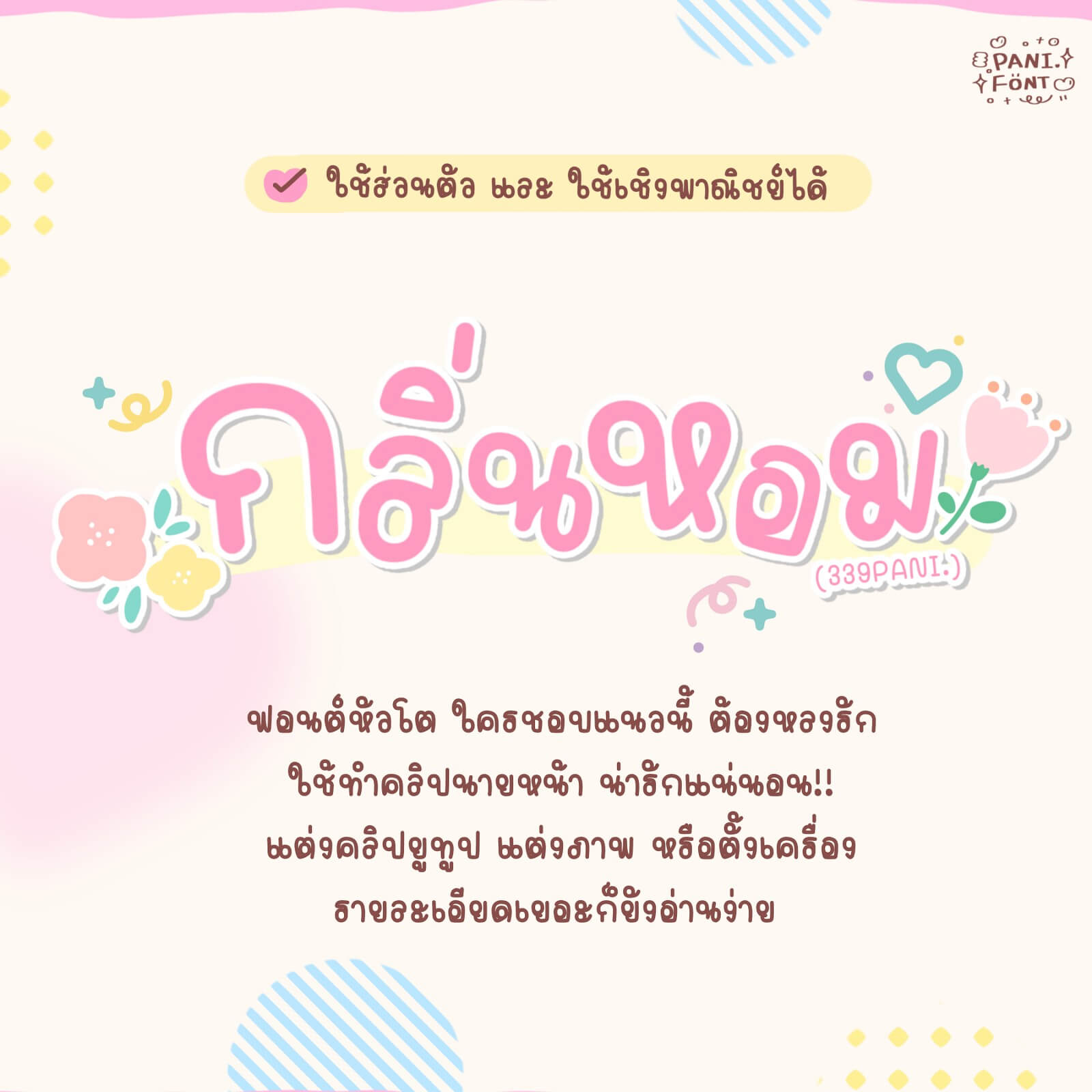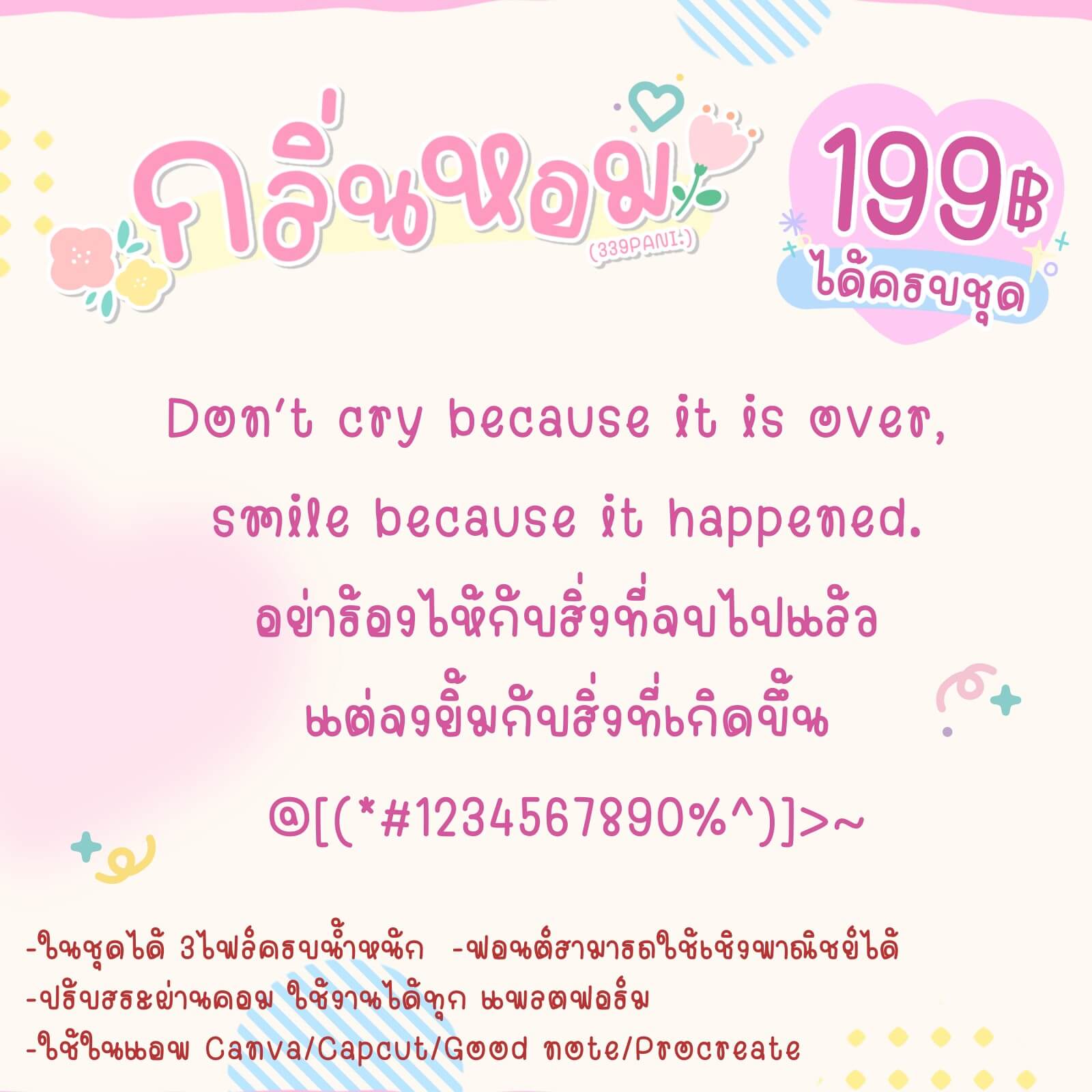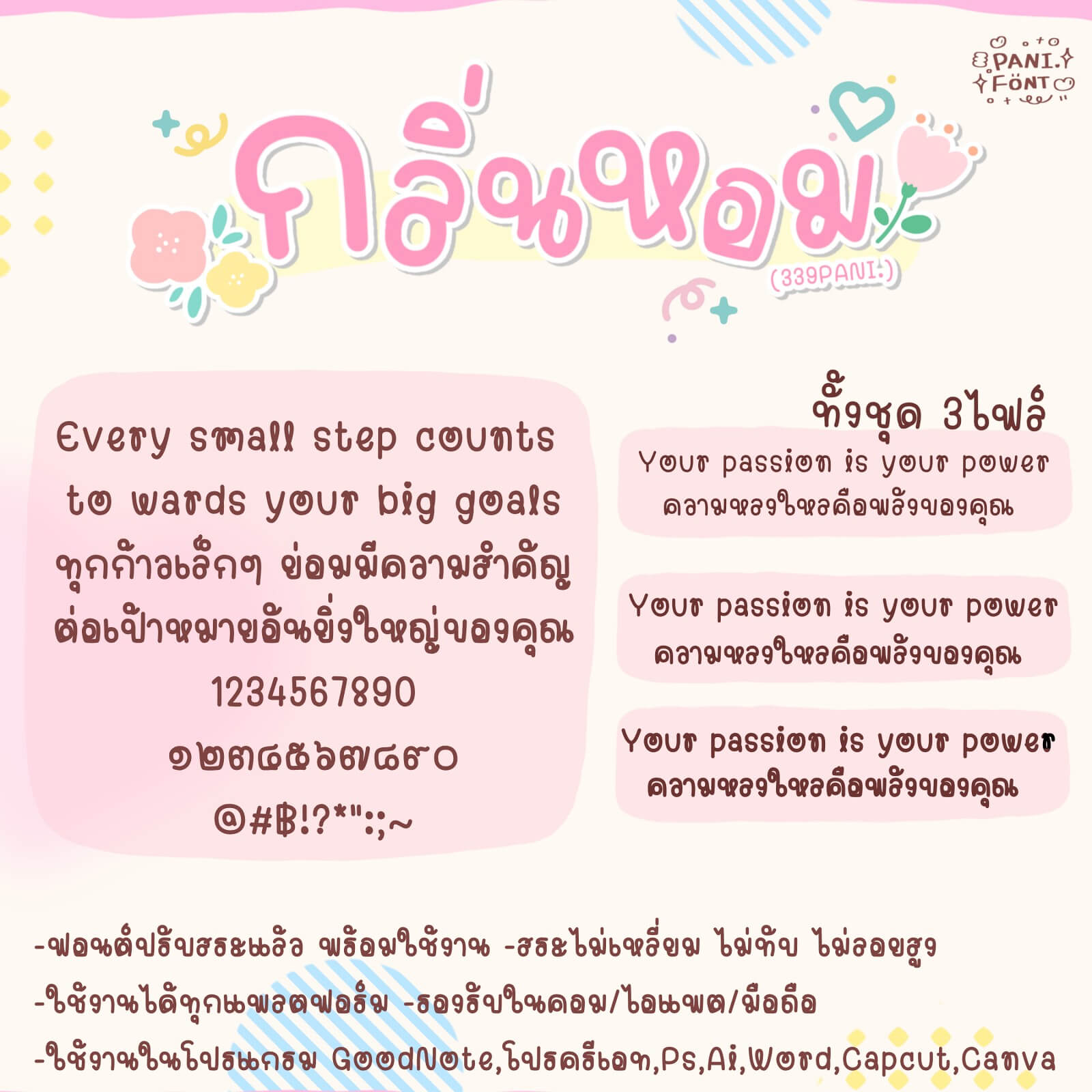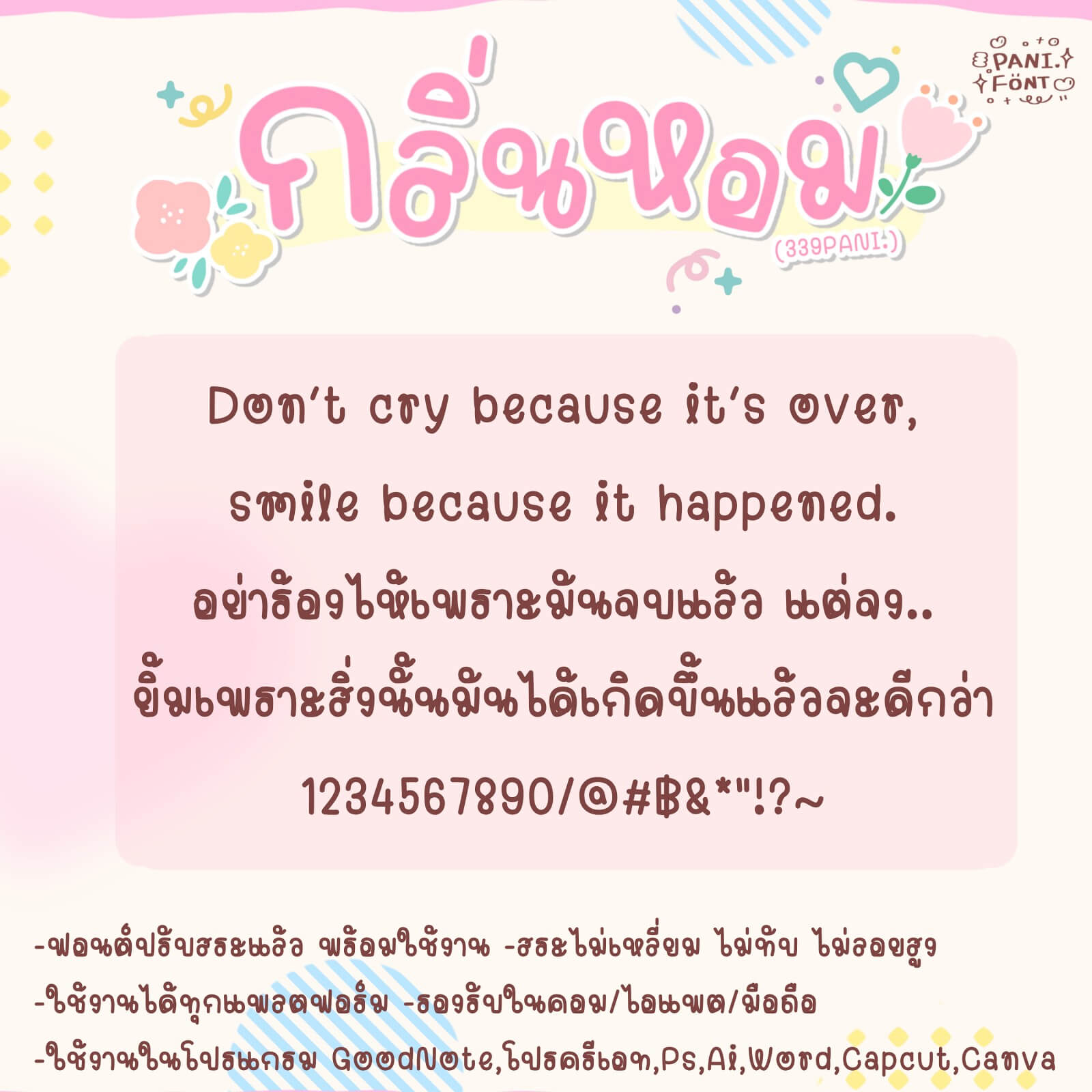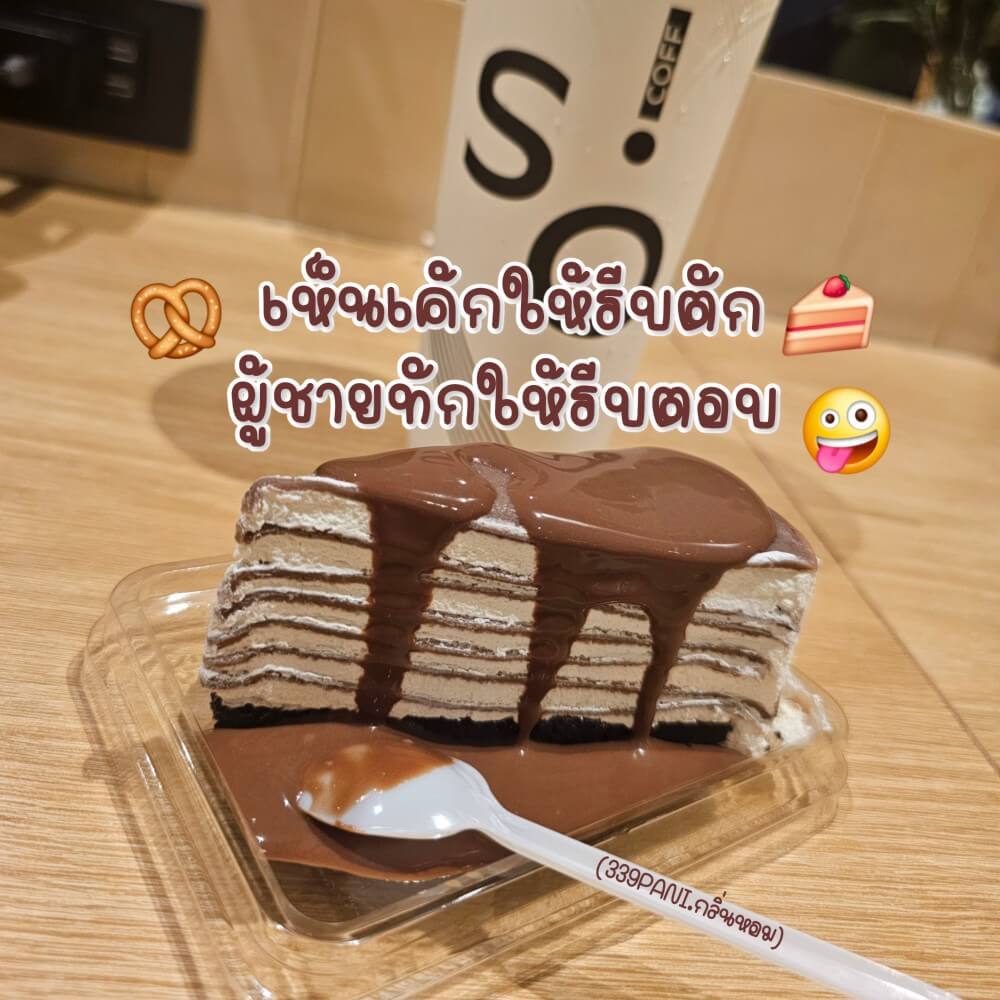
ฟอนต์ PANI.กลิ่นหอม – โหลดทดลองใช้ฟรีตัว Demo ฟอนต์แนวหัวโต ที่เรียบร้อย น่ารัก สายคอนเทนต์/ตั้งเป็นฟอนต์เครื่อง ห้ามพลาด!! เพราะน่ารักมากกกก
PANI.กลิ่นหอม